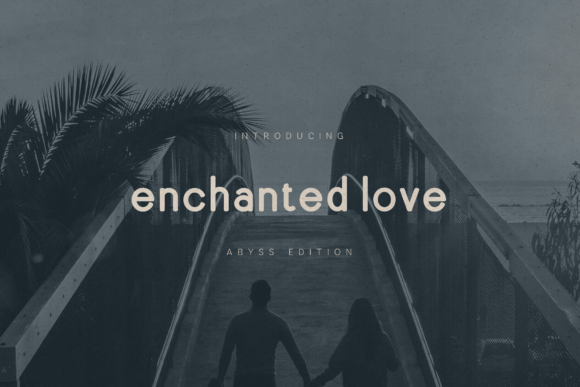
Enchanted Love
إذا كنت تبحث عن أصول عالية الجودة مثل Enchanted Love، فإن هذه الحزمة المميزة هي خيار رائع لمشاريعك الإبداعية.
سواء كنت تقوم بإنشاء منتجات الطباعة عند الطلب أو دعوات الزفاف أو رسومات وسائل التواصل الاجتماعي، فإن Enchanted Love هو الخيار المثالي.